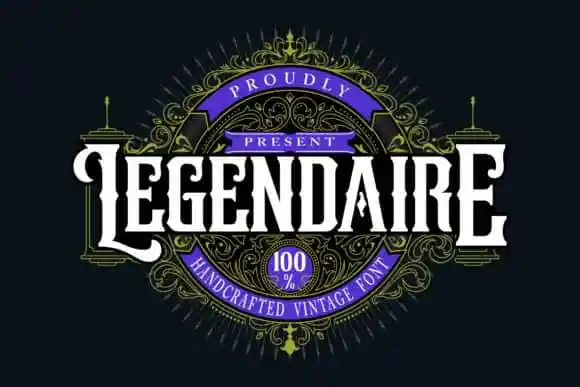
Legendarie Blackletter Font – Download Grátis
A Legendarie Blackletter é uma fonte blackletter que oferece uma experiência visual única e versátil para projetos digitais. Esta fonte é ideal tanto para criações logomarcas quanto para designs de cartazes, selos, capas de livros ou até mesmo camisetas. Seu estilo marcante a torna um recurso imprescindível para quem busca diversidade e originalidade em seus trabalhos. A fonte vem equipada com características do tipo OpenType, como alternativas estilísticas, conjuntos estilísticos e ligaduras, que permitem uma grande flexibilidade ao criar qualquer projeto imaginado. Através da Legendarie Blackletter, você pode trazer vida aos seus projetos digitais, seja ele um design minimalista ou vibrante. Suas alternativas estilísticas são perfeitas para transformar seu layout em algo realmente único e poderoso. Ligaduras elegantes permitem que as letras se unam de maneira atraente em qualquer palavra, tornando o texto mais rico e envolvente. Esses recursos fazem da Legendarie uma fonte excepcionalmente versátil para um grande range de aplicações gráficas, como logotipos, cartazes, selos, capas de livros, camisetas ou embalagens. Descubra a magia do design com Legendarie Blackletter. Seja você uma designer profissional ou iniciante, essa fonte oferece o poder para expressar sua criatividade de maneira inovadora e imprimindo um toque único em suas criações digitais.